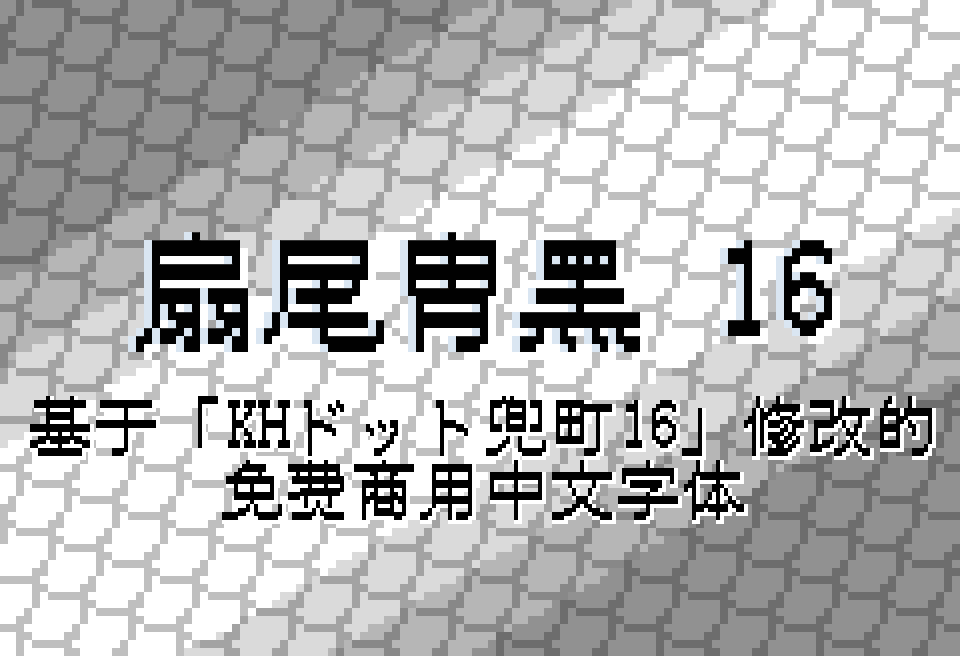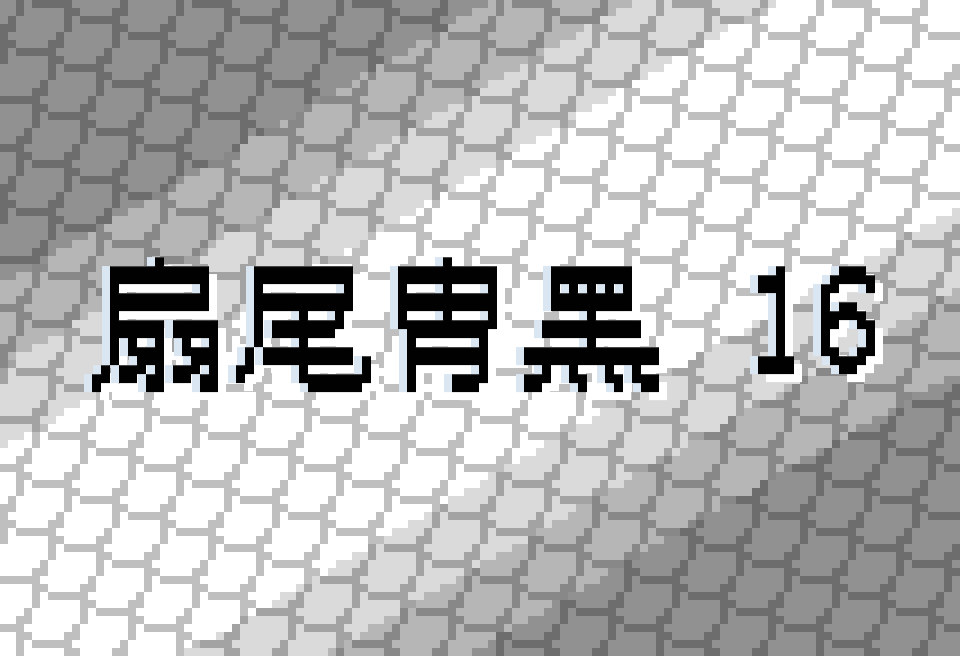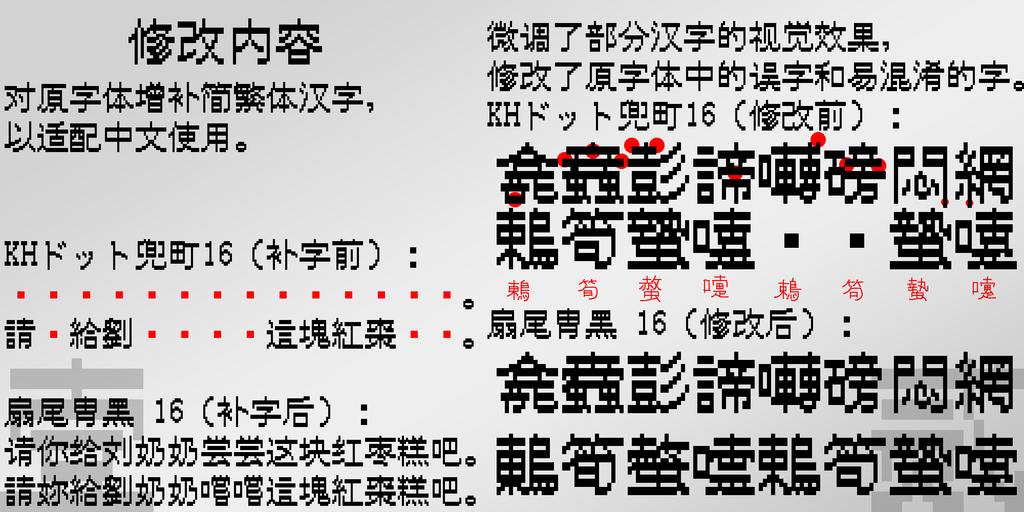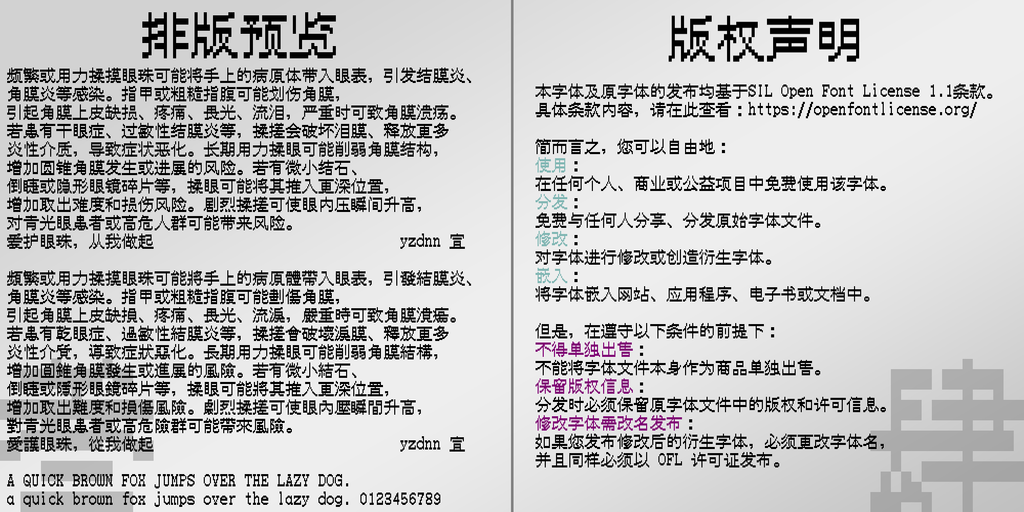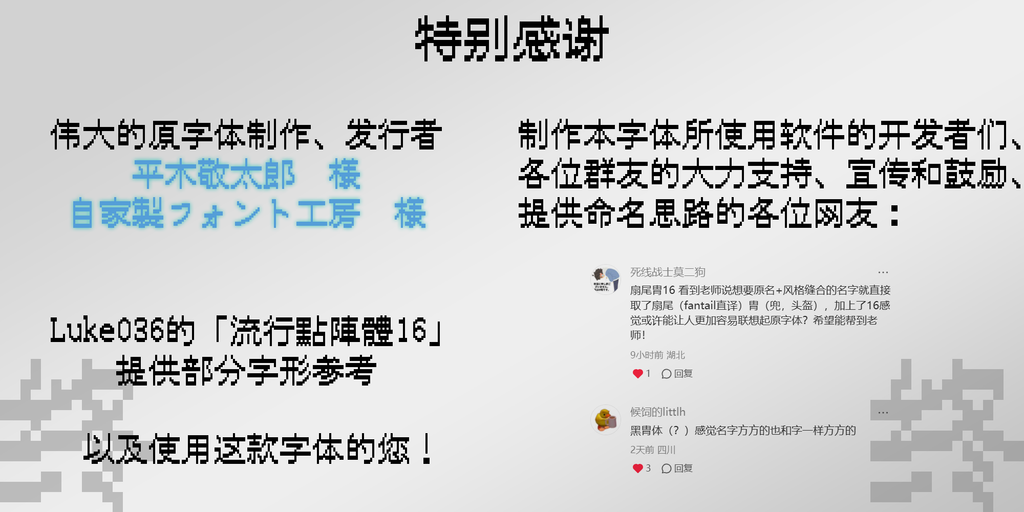
扇尾胄体 16
扇尾胄黑 16是一款基于日文点阵字体 「KHドット兜町16」 进行中文汉字增补与字形调整的16px点阵字体。字体延续了原字体鲜明的像素化视觉特征,并针对中文字符进行了重新补充和修改,让中文汉字也能够融入16px点阵网格之中,整体呈现出厚重、复古且具有强烈数字感的视觉效果。
在字形设计上,扇尾胄黑 16最大的特点是明显的逆反差笔画结构。字体并没有采用常见的横细竖粗形式,而是让横画拥有更加厚实的视觉重量,与竖画形成独特的粗细对比。结合16px有限的像素空间,文字轮廓显得十分硬朗,同时保留了点阵字体特有的方块感和颗粒感。部分笔画经过像素化处理后,会形成具有明显锯齿感的边缘,使字体在小尺寸显示时依然拥有较强的视觉辨识度。
从整体风格来看,扇尾胄黑 16带有比较浓郁的复古游戏与早期数字设备气质。规则的像素网格、厚重的黑色块面以及特殊的笔画比例,让它区别于常见的细腻型点阵字体,更适合需要强调力量感和复古氛围的视觉设计。无论是游戏标题、菜单界面,还是像素风海报、复古网页和数字艺术作品,都能够利用这种独特的像素结构强化画面的风格表现。
字体名称「扇尾胄黑 16」同样来源于原字体与字体风格。“胄”取自原字体名称及日本地名「兜町」中的“兜”,有头盔之意;“扇尾”则来自这种字体风格 Fantail(ファンテール) 的直译。作者将“扇尾”调整至名称前方,并结合字体16px的规格,最终形成了「扇尾胄黑 16」这一具有辨识度的中文字体名称。
在中文字符方面,扇尾胄黑 16主要以简体中文为设计定位,同时对部分繁体汉字进行了增补。字体在制作和修改过程中参考中国大陆字形标准,以G源字形作为主要参考,因此整体更适合简体中文环境下的使用。如果需要进行完整的繁体中文排版,则建议选择专门针对繁体字形制作的流行點陣體16进行搭配。
扇尾胄黑 16尤其适合用于像素艺术、复古游戏、游戏本地化、游戏UI、像素海报、复古网页、程序界面、标题设计以及8-bit、16-bit风格作品等场景。它并不追求传统黑体的标准化视觉,而是通过有限的16px网格重新组织中文笔画,让文字本身成为画面中的视觉元素。用于短标题、标语或界面文字时,能够很好地营造出怀旧、复古、硬朗的像素氛围。
对于喜欢像素字体和复古游戏视觉的设计师来说,扇尾胄黑 16是一款风格非常明确的中文点阵字体。它以16px像素网格为基础,通过横画加粗与逆反差结构塑造出厚重醒目的字形,在保留中文识别度的同时,也赋予文字更加鲜明的复古数字气质,为像素艺术、游戏本地化以及各类复古风格设计提供了一种独特的中文字体选择。